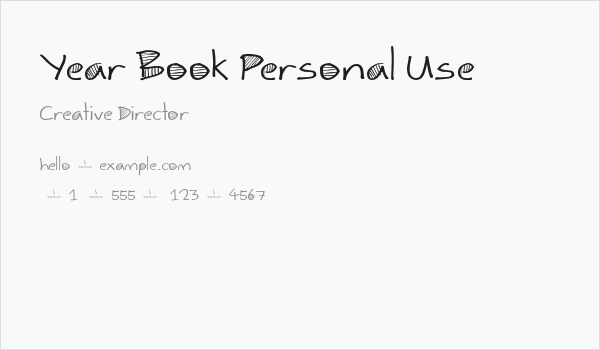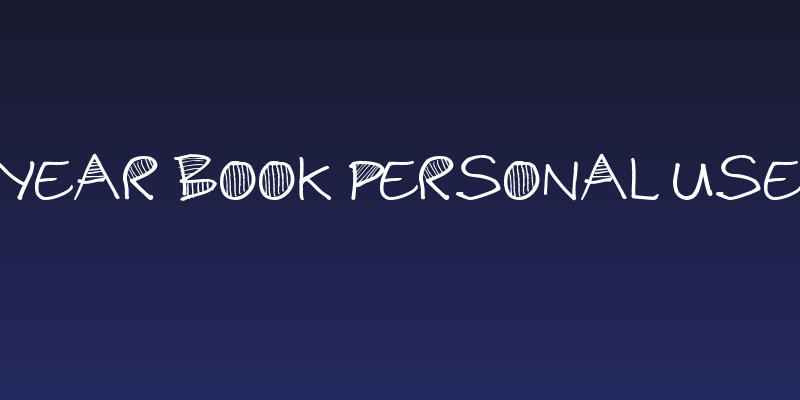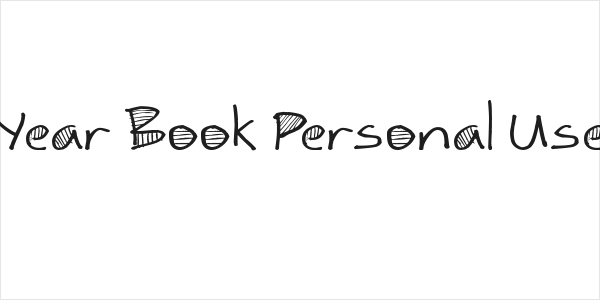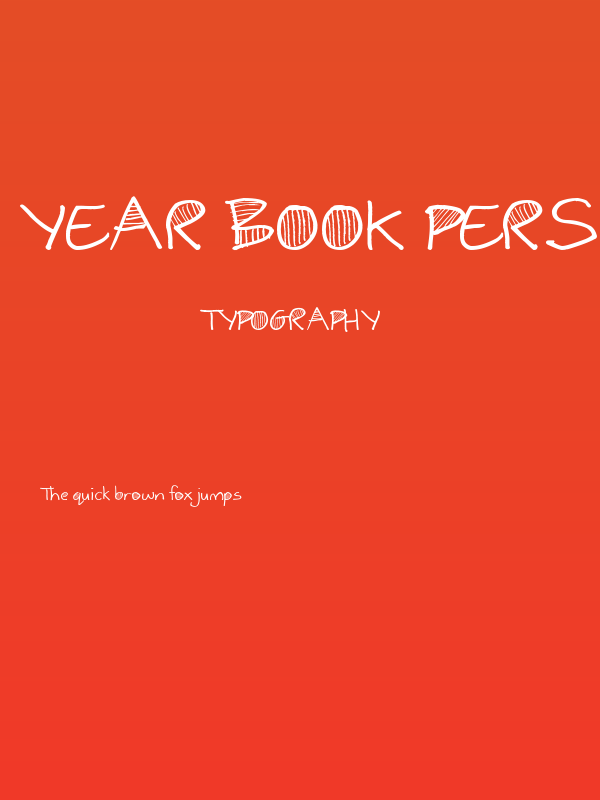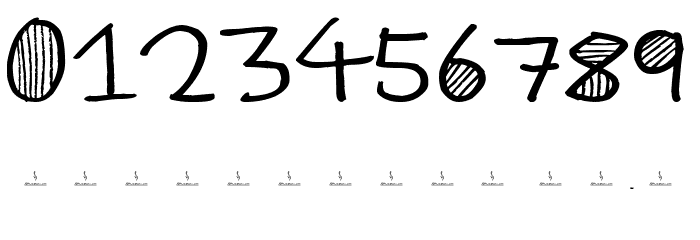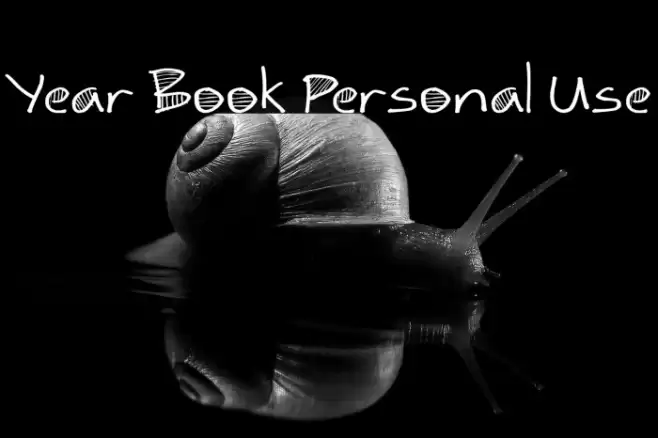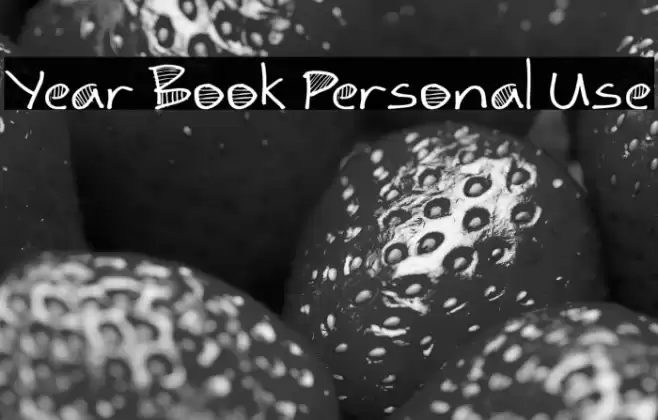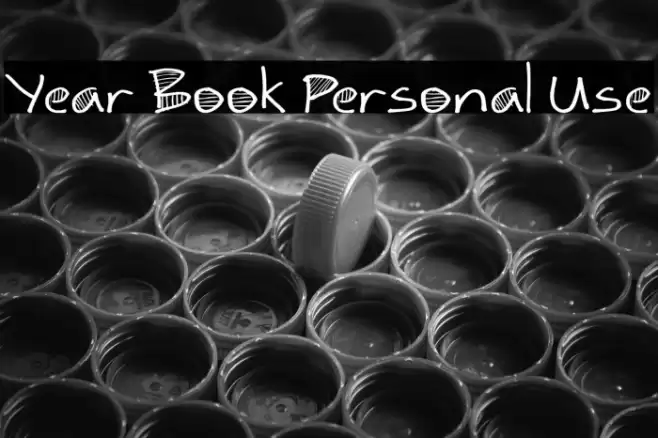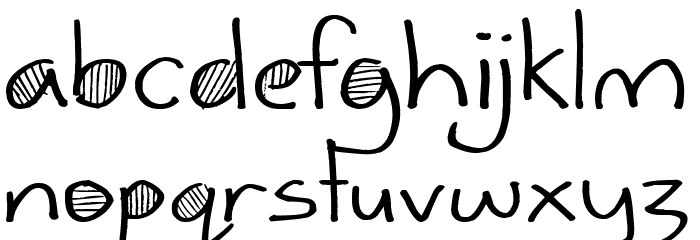
Year Book Personal Use Font
| Gesamtstil | Casual, Creative |
| Anwendungsfall | Headlines, Logos, Informal Text |
| Vorgeschlagene Projekte | Ideal for greeting cards, children's books, personal blogs, and creative branding. |